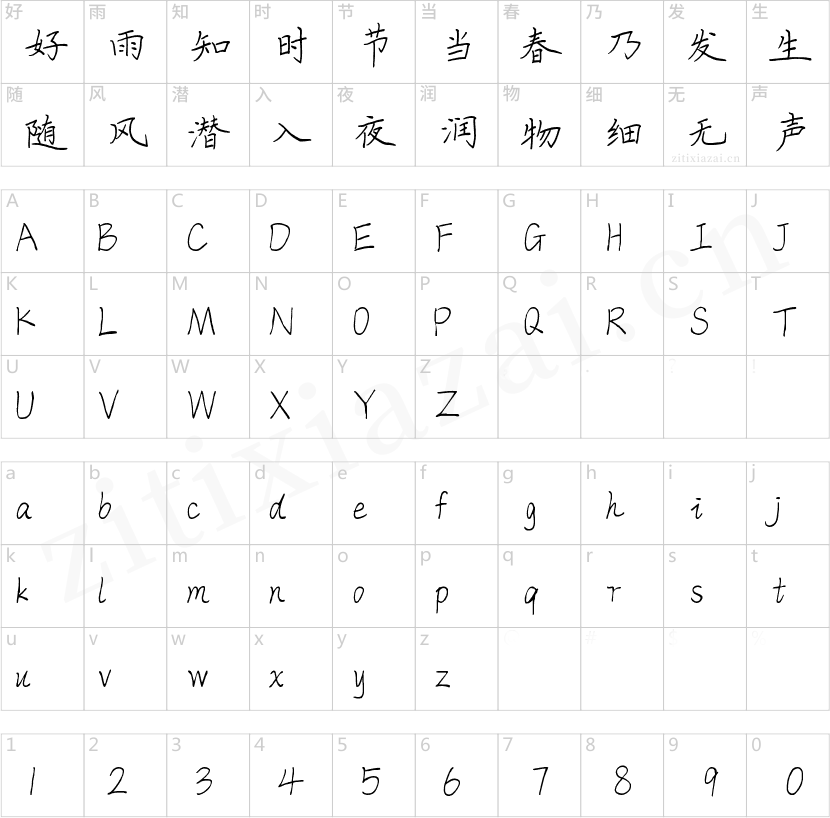
字魂81号-清风体
字魂81号-清风体,这款字体结构工整、笔画清晰,兼顾美观与易读性,适用于标题、正文、海报、包装、LOGO 等多种场景。字形优雅稳定,风格百搭耐看,适配日常排版与创意设计,让文字呈现更舒适、更具质感。字魂81号-清风体一笔一画,皆是细节,以均衡的比例、流畅的线条打造舒适视觉体验,字形端正大气,风格简约现代。无论是商业设计、品牌宣传还是日常排版,都能轻松驾驭,让文字更有格调与力量。字魂81号-清风体字体下载。
字魂字体字小魂清风体字体是由字魂创意字库设计并生产的一款可商用的字体,被收录于字小魂系列。该字体支持GB-2312标准,包含6763个中文、字母、符号和数字,字体类型偏向硬笔手写,具有简约、帅气的风格,在市面上广泛用于电商、社交、广告电商等场景。